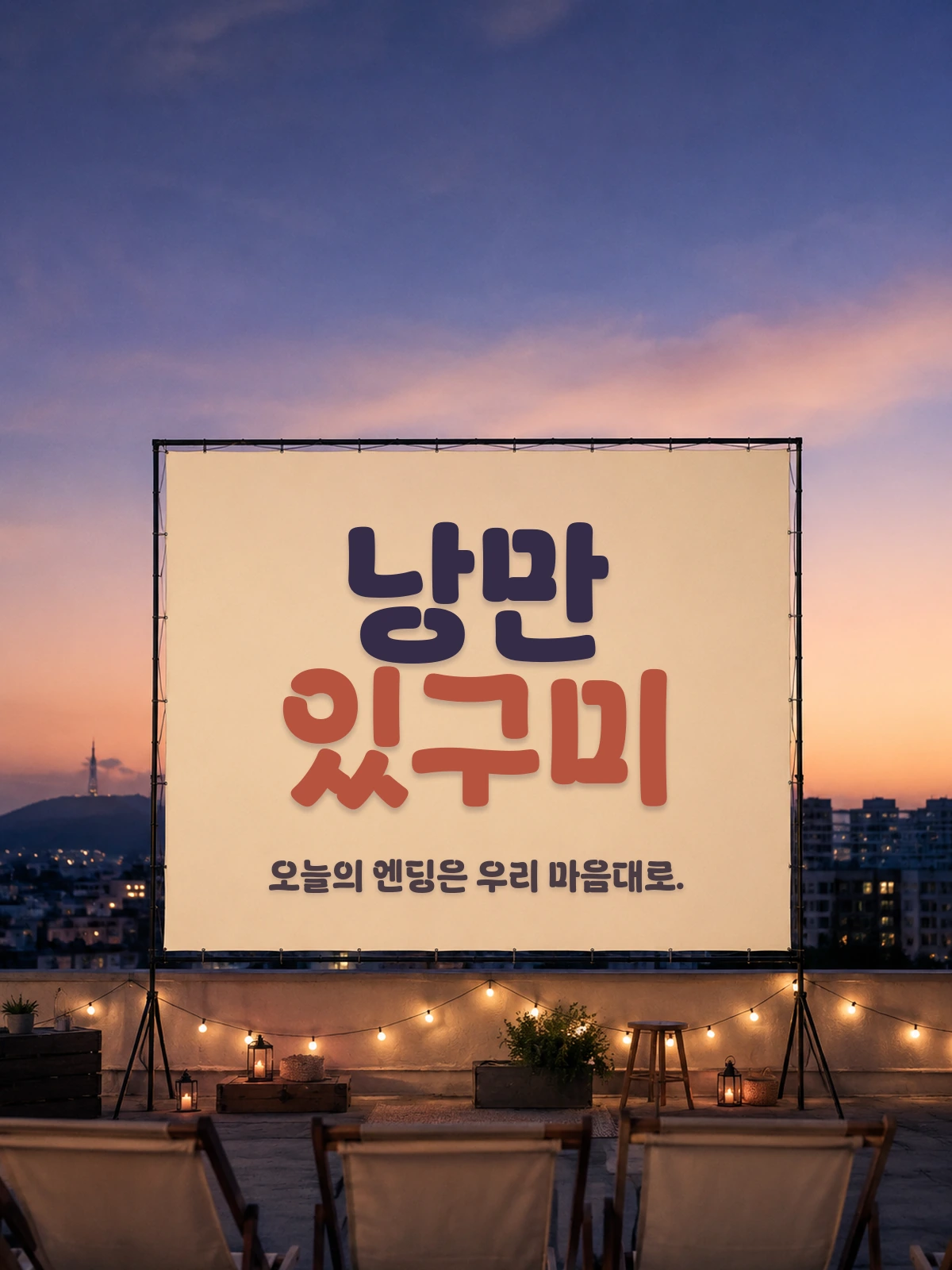
낭만있구미체 — 구미시에서 배포하는 무료 폰트입니다. 굵은 획 위에 곡선을 얹은 고정폭 타이틀용 서체
구미시가 2024년 9월에 공개한 전용서체 세 벌 가운데 타이틀용입니다. 구미첨단산업체, 구미돋움체와 함께 나왔습니다.
만든 과정이 꼼꼼합니다. 시각디자인과 옥외광고 전문가의 의견을 반영해 타이틀용 두 벌과 본문용 한 벌을 정한 뒤, **전 국민을 대상으로 네이밍 선호도 조사를 거쳐 이름을 확정**하고 저작권 등록까지 마쳤습니다. 그러니 낭만있구미는 시의 슬로건이 아니라 공모로 뽑힌 서체 이름입니다.
조형 설명이 세 갈래로 나뉩니다. 우뚝 솟은 ㅅ의 내릿점과 빗침을 통해 구미의 명산 금오산의 장엄한 산줄기와 정기를 담았고, 자연미가 느껴지는 가로획으로 낙동강의 물줄기와 평야를 가로지르는 바람을 표현했으며, 자소의 열린 공간과 둥근 획 마감을 통해 다양한 즐길거리를 제공하는 힐링 문화도시를 나타냈다는 것입니다. 산과 강과 도시를 각각 자소 하나에 배당한 셈입니다.
파일에서 재어 보면 받침 유무에 따른 높이 차가 거의 없는 네모틀이고 자면을 넉넉히 채워 인상이 굵고 단단합니다. 굵기는 하나이고 타이틀용이라 긴 본문에는 맞지 않습니다.